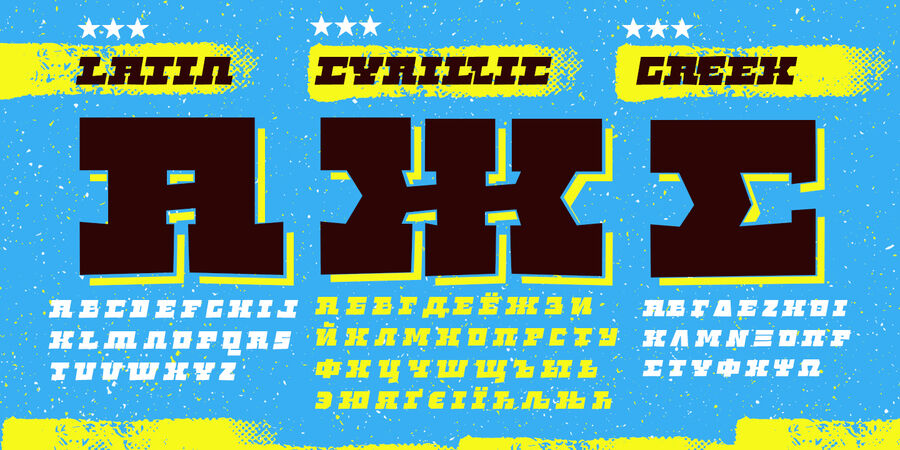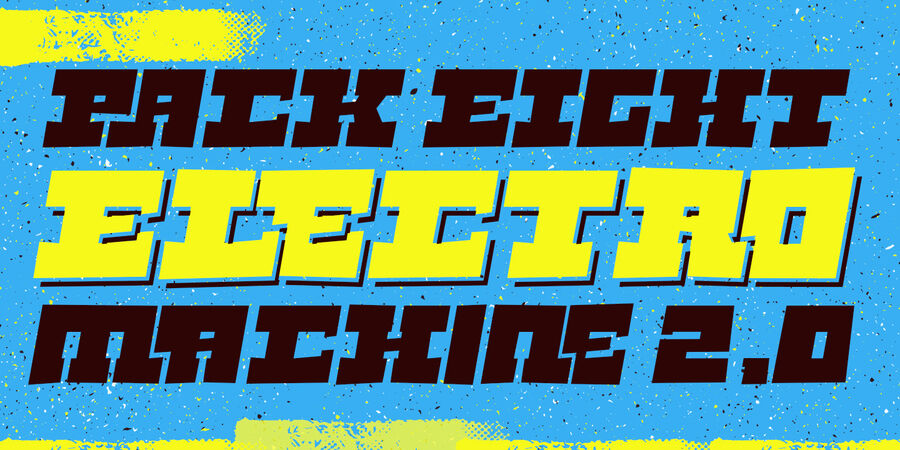
Спайк бот – шрифтове сімейство, спеціально розроблене для виразних назв і заголовків. Підтримує латинку, гречку, кирилицю, містить багато лігатур та альтернатив, щоб зробити дизайн цікавішим. Шрифт розробив Родріго Арая Салас у 2017 році.
Хіт 1990-х Spike Bot підтримує 85 мовУкраїнська, Англійська, Німецька, Польська, Португальська, Іспанська, Французька, Грецька (сучасна), Російська, Чеська, Голландська, Італійська, Шведська, Турецька, Фінська, Білоруська, Грецька, Сербська, Болгарська, Естонська, Литовська, Албанська, Африкаанс, Баскська, Бретонська, Валенсаска, Galician, Гельська (Шотландська), Данська, Індонезійська, Ірландська, Ісландська (Win), Каракалпацька, Каталонська, Норвезька, Окситанська, Ретороманська, Самі Лулі, Тсванська, Узбецька (Лат.), Фарерська, фризька, Чаморро, Естонська (Win), Південносаамська, Албанська (Win), Угорська, Верхньолужицька, Карельська, Латвійська (Mac), Литовська (Mac), Маорійські (Mac), Молдавська (Лат.), Нижньолужицька, Румунська (Win), Словацька, Словенська, Туркменська (Лат.), Хорватська (Win), Естонська (Mac), Курдська, Латишська, Маорійські, Руминська, Абазинська, Аварська, Агульська, Адигейська, Даргинську, Інгуську, Кабардино-Черкеська, Кабардинська, Карачаєво-Балкарська, Кумицька, Лакська, Лезгинська, Македонську, Мордовсько-Мокшанська, Мордовсько-Ерзянська, Ногайська, Рутульська, Табасаранська, Татська, Цахурська, Чеченська Функції сімейства шрифтів Spike BotЗастосування гарнітури у верстці:
плакат, комікс, реклама, журнал, пакування, стінгазета, відео, етикетка, обкладинка, афіша, вивіска, оголошення, стікер, наліпка Адаптованість гарнітури до носіїв:
Асоціації з сімейством шрифтів Spike BotОсобистість і характер гарнітури:
переконливий, чорний, іронічний, значний, квадратний, карикатурний, екстравагантний, мужній, впевнений, суворий, чіткий, щільний, монументальний, залізний, амбітний, стійкий, товстий, наполегливий, тісний, масивний, важкий, громіздкий, дивний, характерний, оригінальний, епатажний, експериментальний, яскравий, активний, крутий, сильний, потужний, твердий, гучний, помітний, нав'язливий, важливий, гострий, небезпечний, екстремальний, сміливий, мачо, ризикований, вуличний, мотивуючий, вибуховий, зухвалий, хуліганський, бандитський, кричущий, кінематографічний, грубий, жорсткий, брутальний, ігровий, тусовочний, двіжняковий, ламаний, агресивний, недбалий, південний, прикольний, молодіжний, виразний, артистичний, грайливий, неохайний, андеграундний, гаражний, міський, смішний, дотепний, мультяшний, студентськиий, прямокутний, радикальний, нахабний, хлоп'ячий, нервовий, запальний, динамічний
кіно, сейф, екскаватор, екшен, шутер, цегла, шахтар, Місто, атракціон, ремонт, конструктор, іграшка, розваги, реклама, інсектицид, гра, закуска, фаст фуд, м'ясо, каскадер, екстрим, бомба, чіпси, кубики, реп, графіті, вечірка, тусовка, скейт, анімація, мультфільм, гараж, монстр, школа, дитяча книжка, ярмарок, шоу, концерт, супергерой, комп'ютерна гра, графіка, ілюстрація, шолом Гарнітура має ознаки стилів: